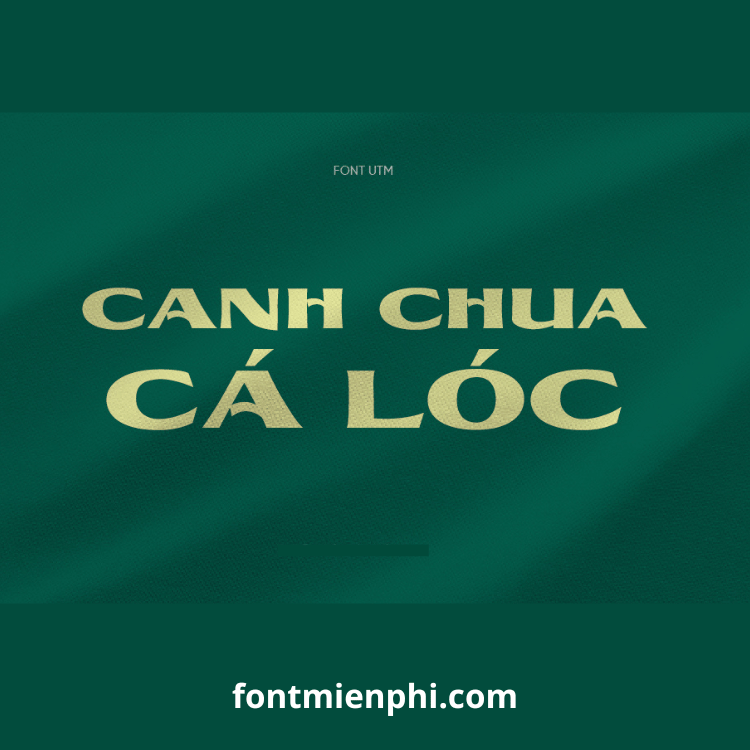
Việt hóa font UTM Brewers KT
Việt hóa font UTM Brewers KT – Phong Cách Retro Độc Đáo Cho Thiết Kế
Giới Thiệu Font UTM Brewers KT Việt Hóa
Font UTM Brewers KT là kiểu chữ retro độc đáo với nét chữ mô phỏng phong cách nhãn bia cổ điển, mang đến vẻ đẹp vintage cho các thiết kế quảng cáo, bao bì và poster. Bản Việt hóa chính thức tại FontMienPhi.com đã được tối ưu đầy đủ bộ dấu tiếng Việt, giúp bạn thoải mái sáng tạo mà không lo lỗi font.
Đặc Điểm Nổi Bật Của Font
✔ Phong cách vintage độc đáo – Hoàn hảo cho thiết kế nhãn hiệu, quảng cáo
✔ Nét chữ đậm, góc cạnh – Tạo điểm nhấn ấn tượng